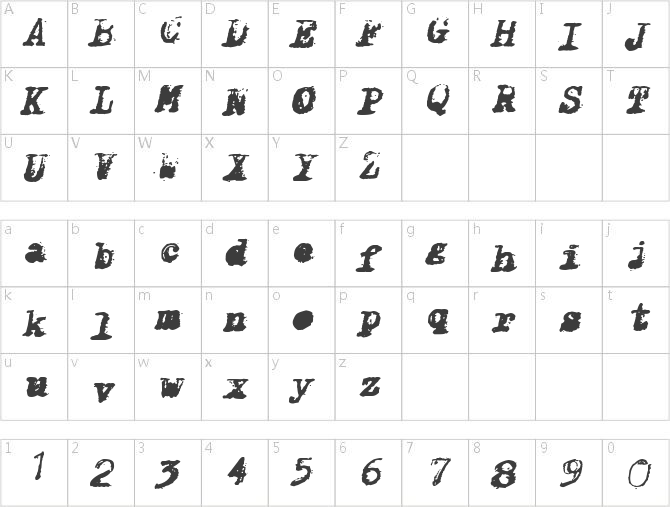
X-Classified Italic 詳情頁(yè)
X-Classified Italic字體字庫(kù)是一款讓人賞心悅目、百看不厭的英文字體,適合各類廣告和產(chǎn)品包裝設(shè)計(jì)應(yīng)用,字體大小0.08MB,格式為ttf字體,上傳用戶是小北,作者/版權(quán)方為未知